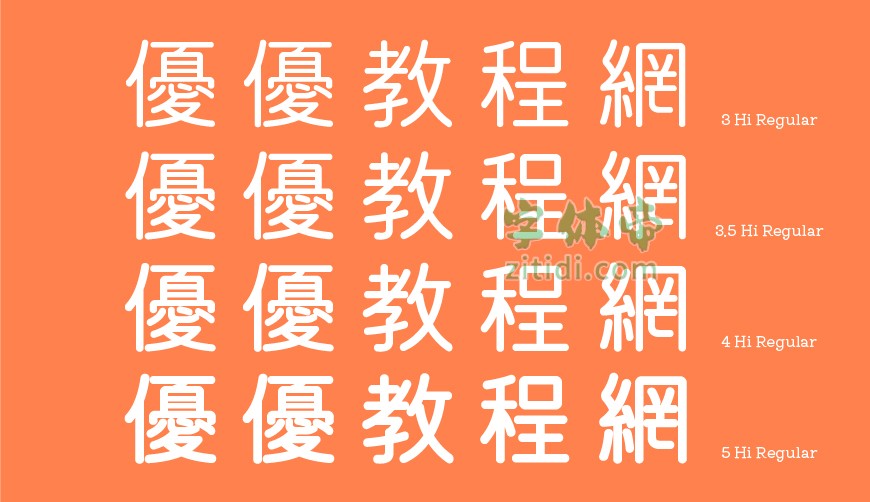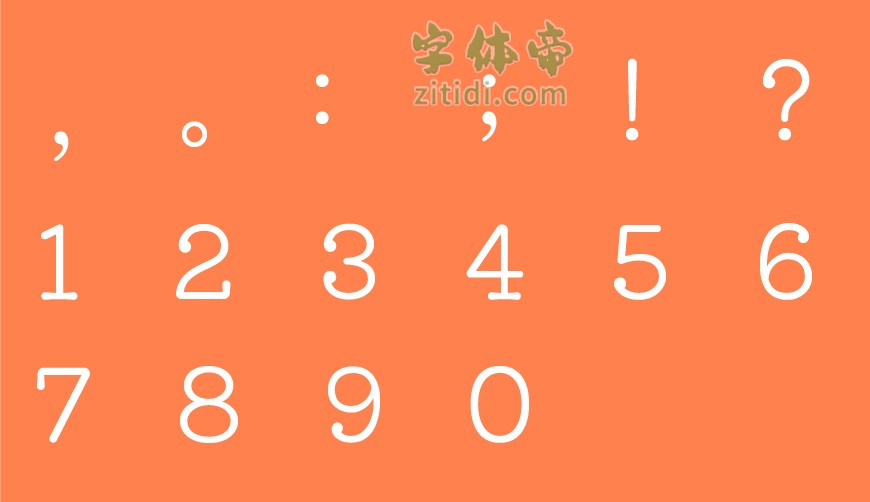
虽说这是一款日文字体,但是收录超过6,600个字 (JIS第1水准2965字,第2水准3390字) ,等于说支持灰常灰常多的中文字,而且用起来的样式可爱可爱的,一点都不输给 「 濑户字体 」 ,当然这还是取决于大家自己的喜好啦!如果喜欢这款字体就赶紧下载吧!
“哈密瓜体 5 Hi”是一款书写很新颖的字体,字体大方,适合各种设计作品使用!欢迎下载!